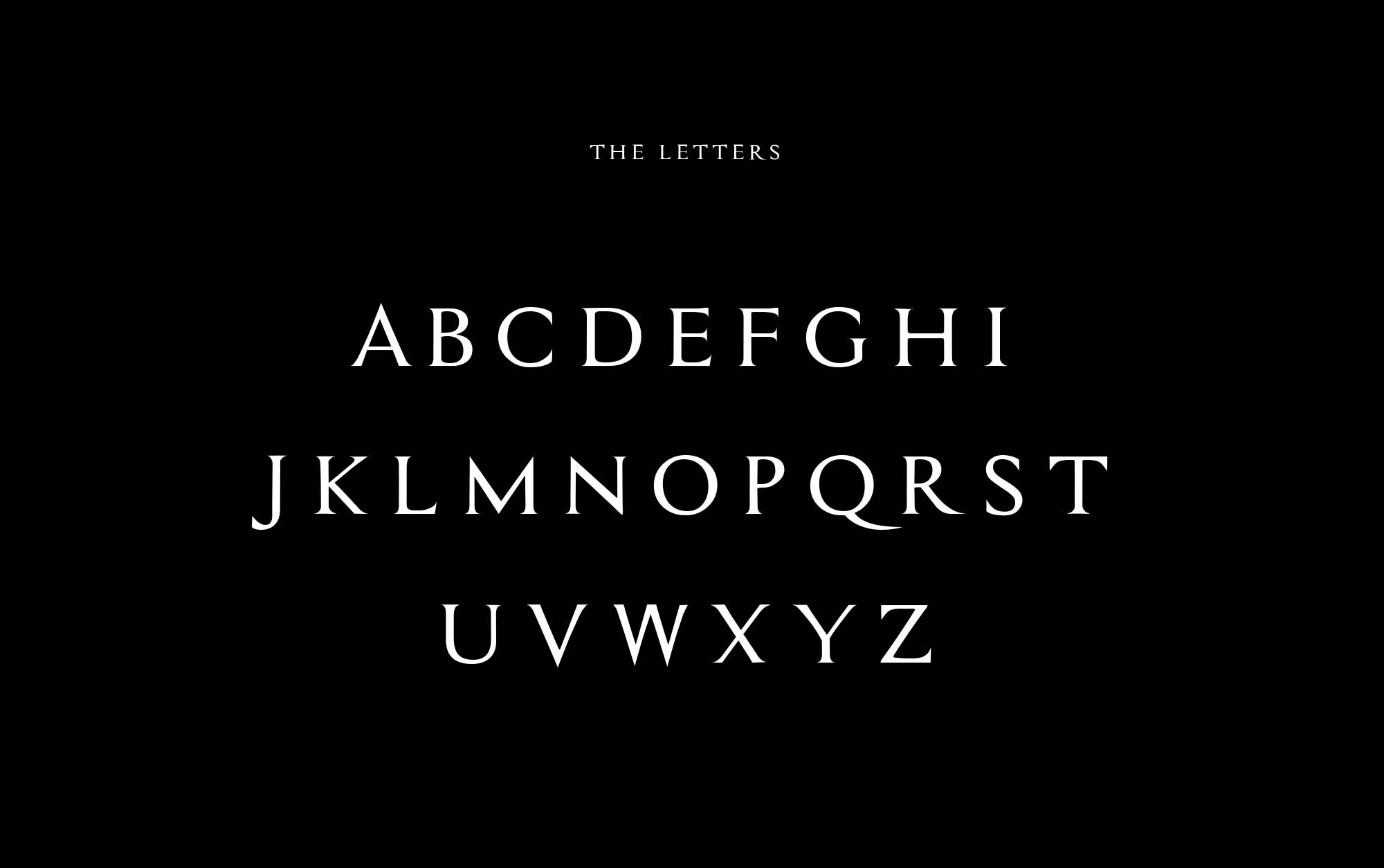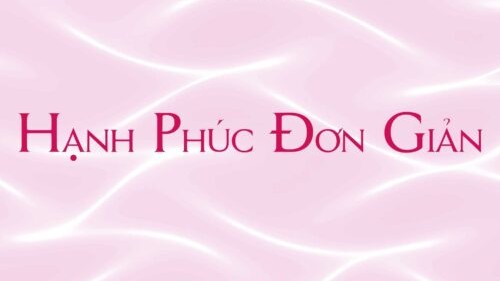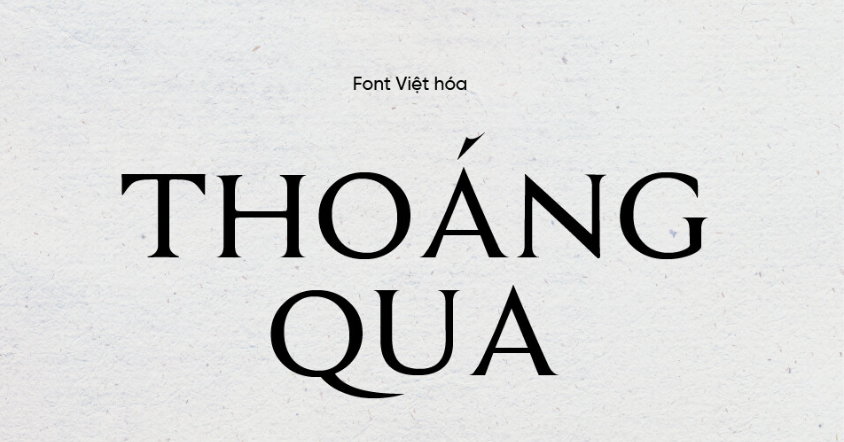
Font UVF Assassin là bộ phông chữ thuộc dòng Display mang phong cách hành động, sắc lạnh và đậm chất viễn tưởng (Sci-fi/Gaming), nổi bật với những đường cắt vát sắc nhọn mô phỏng lưỡi kiếm của các sát thủ bóng đêm. Được đội ngũ UVF tinh chỉnh hoàn thiện hệ thống dấu tiếng Việt, phông chữ này là vũ khí thị giác tuyệt vời cho các thiết kế logo gaming gear, poster phim hành động, giải đấu thể thao điện tử (E-sports) và bao bì phụ kiện công nghệ hầm hố. Doozypack.vn chia sẻ link download font UVF Assassin chuẩn kỹ thuật, giúp bạn sở hữu phông chữ cực chất mà không lo gặp bất kỳ lỗi hiển thị dấu thanh nào khi thiết kế in ấn.
Đặc điểm thẩm mỹ độc đáo của Font UVF Assassin
UVF Assassin không đi theo sự an toàn của các phông chữ hình học truyền thống; nó tạo ra một ngôn ngữ thị giác đầy tính đe dọa, uy lực và tràn đầy sự kịch tính.
Đường nét góc cạnh sắc bén mô phỏng lưỡi kiếm
Đặc trưng lớn nhất của Font UVF Assassin là các góc nhọn và đường vát chéo dứt khoát ở các điểm đầu và đuôi chữ cái. Thiết kế này gợi liên tưởng trực tiếp đến những món vũ khí cận chiến sắc bén, mang lại cảm giác nguy hiểm, bí ẩn và cực kỳ mạnh mẽ. Khi đặt UVF Assassin làm tiêu đề trên bao bì, tên sản phẩm của bạn sẽ ngay lập tức tạo ra một sức hút thị giác dữ dội, đặc biệt thu hút cộng đồng game thủ và những người đam mê phong cách Cyberpunk cá tính.
Cấu trúc hình khối mạnh mẽ và đậm chất điện ảnh
Các ký tự của UVF Assassin sở hữu độ dày nét đồng đều, tỷ lệ chữ vuông vức vững chãi tạo nên sự đĩnh đạc và chắc chắn. Dù có nhiều chi tiết cắt xẻ táo bạo, phông chữ vẫn giữ được trục thẳng đứng chuẩn mực, giúp các dòng tiêu đề trên vỏ hộp hiển thị rõ ràng, không bị méo mó hay khó đọc khi quan sát từ khoảng cách xa.
- Khắc phục triệt để lỗi dấu tiếng Việt: Phiên bản Việt hóa của UVF Assassin đã được trau chuốt thủ công từng dấu câu. Các dấu sắc, huyền, hỏi, ngã, nặng được vát nhọn đồng điệu với cấu trúc gai góc của thân chữ, không tạo cảm giác chắp vá hay làm mất đi tính sắc lạnh nguyên bản.
03 Ứng dụng thực tế của font UVF Assassin trong sản xuất bao bì
Sự sắc lạnh và uy lực của UVF Assassin mang lại hiệu ứng thị giác đắt giá trên các dòng sản phẩm bao bì thực tế do Doozypack.vn sản xuất:
- Hộp đựng phụ kiện Gaming (Chuột, Bàn phím, Tai nghe): Tiêu đề thương hiệu in bằng font Assassin kết hợp kỹ thuật in phủ UV định hình trên giấy Ivory đen tạo nên vẻ ngoài vô cùng cao cấp và đậm chất công nghệ.
- Bao bì đồ uống tăng lực & Nước giải khát thể thao: Nét chữ góc cạnh mô phỏng năng lượng bùng nổ, giúp nhãn dán lon hoặc chai lọ toát lên vẻ mạnh mẽ và lôi cuốn giới trẻ.
- Túi giấy thời trang Streetwear: Dùng cho tên thương hiệu in trên nền túi giấy tối màu mang lại phong cách bụi bặm, nổi loạn và tạo dấu ấn nhận diện độc bản.